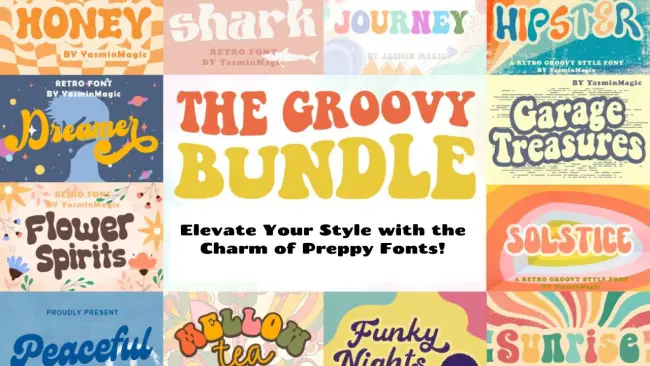
프레피 폰트의 매력으로 스타일을 업그레이드해보세요!
모든 픽셀과 곡선이 중추적인 역할을 하는 역동적인 디자인 영역에서 글꼴의 중요성은 아무리 강조해도 지나치지 않습니다. 글꼴은 단어에 생명을 불어넣어 브랜드와 개인 모두의 시각적 내러티브를 형성하는 숨은 영웅입니다.
타이포그래피의 우아함을 탐구하면서 우리는 세련됨과 유쾌함을 자연스럽게 결합한 독특한 장르인 "Preppy Fonts" 의 매혹적인 세계를 탐구합니다. 화면이나 페이지의 단순한 글자를 넘어, 프레피 글꼴은 전통적인 경계를 뛰어넘는 디자인 철학을 구현합니다.
의도적인 글꼴 선택은 종종 눈에 띄지 않는 방식으로 스타일과 미적 매력에 영향을 미치는 조용한 오케스트레이터가 될 수 있습니다. "Preppy Fonts" 에 담긴 매력을 풀고 디자인의 시각적 언어에 미치는 심오한 영향을 탐구하면서 글꼴의 정교함이 중심이 되는 여정에 동참하세요.
Preppy 글꼴 공개
디자인 세계에서 조용하지만 강력한 커뮤니케이터인 타이포그래피는 "프레피 폰트"에서 그 매력과 세련미를 구현합니다. 이 섹션에서는 프레피 글꼴을 인기 있는 선택으로 만드는 뚜렷한 특징과 뉘앙스를 설명하고 프레피 글꼴의 정의, 특징, 차별화되는 고유한 특성을 검토합니다.
프레피 폰트의 정의와 특징
프레피 글꼴의 핵심은 시대를 초월한 우아함과 현대적인 즐거움의 융합을 보여줍니다. 깔끔한 선, 날카로운 모서리, 세련된 미학으로 정의된 이 글꼴은 세련된 라이프스타일의 본질을 담고 있습니다.
프레피 글꼴의 특징에는 질서정연함, 형식적인 느낌, 다양한 디자인 상황에 대한 다재다능한 적응성이 포함되는 경우가 많습니다.
클래식하면서도 현대적인 분위기를 전달하는 능력 덕분에 프레피 글꼴은 전통 미학과 현대 미학 사이의 균형을 맞추려는 디자이너에게 역동적인 선택이 됩니다.
인기 있는 Preppy 글꼴의 예
프레피 글꼴의 폭과 다양성을 진정으로 이해하려면 구체적인 예를 살펴보는 것이 중요합니다. 시대를 초월한 세리프체를 지닌 "Garamond" 나 높은 대비와 수직 강세로 유명한 "Bodoni" 와 같은 글꼴은 프레피 글꼴 미학의 예입니다. “Helvetica Neue”는 깔끔하고 현대적인 외관으로 유명한 또 다른 다목적 프레피 글꼴입니다.
이러한 각 예는 프레피 글꼴 카테고리에 독특한 풍미를 더해주며, 이 스타일이 독특한 매력을 유지하면서 다양한 디자인 요구 사항에 어떻게 적응할 수 있는지 보여줍니다.
Preppy 글꼴은 다른 타이포그래피 스타일과 어떻게 다른가요?
프레피 글꼴은 우아함을 추구하는 동시에 미묘하면서도 영향력 있는 방식으로 다른 타이포그래피 스타일과 차별화됩니다. 고정폭 글꼴의 구조화된 균일성과 비교하여 프레피 글꼴은 더욱 역동적이고 표현력이 풍부한 시각적 경험을 제공합니다.
손글씨 스크립트 글꼴의 유려하고 개인화된 특성과 달리 프레피 글꼴은 세련되고 세련된 느낌을 유지합니다. 이 섹션에서는 프레피 글꼴을 돋보이게 만드는 특정 속성을 자세히 살펴보고 다른 타이포그래피 스타일과 비교하여 적응성과 독특한 디자인 기여도를 강조합니다.
프레피 폰트의 매력
타이포그래피 영역에서 “Preppy Fonts”의 매력은 단순한 시각적 요소를 넘어 확장됩니다. 이는 시대를 초월한 매력, 문화적 중요성, 브랜드 아이덴티티에 대한 영향력 있는 역할을 반영하는 독특한 매력을 담고 있습니다.
시대를 초월한 프레피 미학의 매력 탐구
프레피 글꼴의 중심에는 디자인 트렌드를 초월하는 시대를 초월한 매력이 있습니다. 깔끔한 라인, 균형 잡힌 비율, 세심한 디테일은 수십 년 동안 지속되는 미학에 기여합니다.
프레피 글꼴에 내재된 단순함과 우아함은 클래식한 세련미를 자신의 작품에 불어넣고자 하는 디자이너에게 영원한 선택이 됩니다. 끊임없이 진화하는 디자인 환경에서 프레피 글꼴은 지속적인 스타일의 확고한 상징으로 자리잡고 있습니다.
문화 협회와 프레피 스타일의 역사
프레피 글꼴의 매력을 진정으로 이해하려면 프레피 스타일의 문화적 연관성과 풍부한 역사를 탐구해야 합니다.
20세기 초 엘리트 아이비리그 대학에서 시작된 프레피 스타일은 세련미, 교육, 절제된 럭셔리함의 대명사가 되었습니다.
이러한 문화적 배경은 프레피 글꼴에 명성과 전통을 불어넣어 미학을 전달할 뿐만 아니라 현대와 시대를 초월한 것을 연결하는 역사적인 이야기를 전달하는 선택이 됩니다.
Preppy 글꼴이 브랜드 아이덴티티와 커뮤니케이션을 강화하는 방법
브랜딩 비즈니스에서는 모든 세부 사항이 중요하며 글꼴 선택은 브랜드 아이덴티티와 커뮤니케이션을 형성하는 데 중추적인 역할을 합니다. 세련되고 세련된 분위기를 지닌 프레피 글꼴은 세련미와 신뢰성을 전달하려는 기업에 다양한 도구를 제공합니다.
마케팅 자료, 로고, 디지털 콘텐츠 등 무엇에서든 프레피 글꼴을 사용하면 전문성과 세부 사항에 대한 관심을 전달하는 시각적 언어를 구축할 수 있습니다. 고정폭 글꼴의 뚜렷한 균일성이나 손글씨 스크립트 글꼴의 개인화된 터치와는 대조적으로, 프레피 글꼴은 독특한 브랜드 특성을 유지하면서 광범위한 청중의 관심을 끌 수 있는 균형을 유지합니다.
디자인에 Preppy 글꼴 통합하기
“Preppy Fonts”를 디자인에 통합하려면 글꼴의 특성뿐만 아니라 다양한 디자인 요소와의 원활한 정렬을 고려하는 미묘한 접근 방식이 필요합니다.
이 섹션에서는 프레피 글꼴을 디자인 프로젝트에 통합할 때 효과적인 전략, 성공적인 예, 필수 해야 할 일과 하지 말아야 할 일을 살펴봅니다.
Preppy 글꼴을 다양한 디자인 요소와 결합하는 팁
프레피 글꼴을 다른 디자인 요소와 결합하려면 균형과 조화에 대한 예리한 안목이 필요합니다. 대담한 프레피 글꼴과 세련되고 미니멀한 레이아웃을 대조하여 눈에 띄는 시각적 효과를 만들어보세요.
또는 세리프 프레피 글꼴과 우아한 일러스트레이션을 결합하면 고전적인 세련미를 불러일으킬 수 있습니다. 가독성과 전반적인 시각적 매력을 향상시키는 보완적인 대비를 위해 노력하십시오.
고정 폭 글꼴의 엄격한 균일성이나 손글씨 스크립트 글꼴의 흐르는 듯한 특성과 달리 프레피 글꼴은 페어링에 유연성을 제공하므로 광범위한 디자인 응용 프로그램에 적합합니다.
Preppy 글꼴을 사용한 성공적인 디자인 프로젝트의 예
프레피 글꼴이 다양한 디자인 상황에서 어떻게 빛날 수 있는지 이해하려면 실제 사례를 검토하는 것이 중요합니다. J.Crew 및 Ralph Lauren과 같은 브랜드는 프레피 글꼴을 활용하여 시대를 초월한 우아함을 전달하고 로고, 포장 및 마케팅 자료에 원활하게 통합합니다.
웹 디자인에서 Pinterest와 같은 플랫폼은 프레피 글꼴을 사용하여 깨끗하고 세련된 미학을 유지하여 향상된 사용자 경험에 기여합니다. 이러한 예는 다양한 업계에 걸쳐 프레피 글꼴의 다양성을 보여주고 브랜드 아이덴티티를 전달하는 데 있어 그 효과를 보여줍니다.
Preppy 글꼴을 사용할 때 해야 할 일과 하지 말아야 할 일
프레피 글꼴을 성공적으로 통합하려면 해야 할 일과 하지 말아야 할 일을 따르는 것이 중요합니다.
- 명확한 글자체와 적절한 간격을 갖춘 프레피 글꼴을 선택하여 가독성을 우선시하세요.
- 브랜드의 개성에 맞는 조합을 찾으려면 글꼴 조합을 실험해 보세요.
- 장식 요소를 과도하게 사용하지 마십시오. 고유한 우아함을 지닌 프레피 글꼴은 그 자체로 돋보일 때 빛을 발하는 경우가 많습니다.
- 계층 구조와 일관성의 중요성을 무시하지 마십시오. 다양한 디자인 요소에 걸쳐 응집력 있는 모양을 유지하여 전반적인 효과를 향상시킵니다.
디자이너는 이러한 해야 할 일과 하지 말아야 할 일을 준수함으로써 프레피 글꼴의 잠재력을 최대한 활용하여 시각적으로 매력적이고 효과적인 디자인 프로젝트를 만들 수 있습니다.
디지털 시대의 프레피 글꼴
컴퓨터화된 장면을 탐색하면서 "Preppy Text 스타일" 작업이 현대 계획의 요구 사항을 충족하도록 개발되었습니다.
이 세그먼트에서는 웹 및 고급 계획에서 프레피 텍스트 스타일의 중요성을 조사하고, 이러한 텍스트 스타일을 찾고 사용하기 위한 장치 및 자산에 대한 약간의 지식을 제공하며, 프레피 텍스트 스타일이 가상 엔터테인먼트 및 사이트의 느낌을 어떻게 향상시킬 수 있는지 자세히 알아봅니다.
온라인 및 디지털 디자인에서 Preppy 글꼴의 관련성
화면이 지배하는 시대에 프레피 글꼴은 고전적인 미학과 현대적인 매력을 완벽하게 결합하여 관련성을 유지합니다. 프레피 글꼴 고유의 깔끔한 라인과 시대를 초월한 우아함은 온라인 및 디지털 플랫폼으로 원활하게 변환되어 세련되고 정교한 사용자 경험에 기여합니다.
프레피 글꼴의 적응성은 웹사이트 제목부터 소셜 미디어 그래픽에 이르기까지 다양한 디지털 애플리케이션에서의 효율성을 보장합니다. 고정 폭 글꼴의 실용적인 성격이나 손글씨 스크립트 글꼴의 비공식적인 매력과 달리 프레피 글꼴은 디지털 영역에서 잘 어울리는 전문성을 제공합니다.
Preppy 글꼴을 찾고 사용하기 위한 도구 및 리소스
디지털 프로젝트에 적합한 프레피 글꼴을 찾으려면 다양한 서체에 액세스해야 합니다. 다행히도 수많은 도구와 리소스가 프로세스를 단순화합니다. Google Fonts 및 Adobe Fonts와 같은 플랫폼은 디지털 디자인에 쉽게 통합할 수 있는 광범위한 프레피 글꼴을 제공합니다.
디자이너는 글꼴 라이브러리를 탐색하여 디지털 인터페이스 및 반응형 디자인과의 호환성을 보장할 수 있습니다. 프레피 글꼴의 다양성은 실험과 사용자 정의를 가능하게 하여 디자이너가 디지털 창작물에 완벽하게 어울리는 글꼴을 찾을 수 있도록 해줍니다.
Preppy 글꼴이 소셜 미디어와 웹사이트 미학을 향상시키는 방법
소셜 미디어와 웹사이트 디자인의 역동적인 세계에서 프레피 글꼴은 관심을 끌고 브랜드 미학을 향상시키는 독특한 터치를 제공합니다.
소셜 미디어 그래픽, 배너, 웹 사이트 제목에 프레피 글꼴을 활용하면 전체적인 시각적 매력을 향상시켜 일관되고 기억에 남는 브랜드 아이덴티티를 만들 수 있습니다. 프레피 글꼴의 구조화된 특성은 디지털 화면의 가독성에 기여하여 긍정적인 사용자 경험을 보장합니다.
결론
디자인의 교향곡에서 우리는 "Font Finesse: 프레피 글꼴의 매력으로 스타일 향상"의 뉘앙스를 살펴보았습니다. 프레피 글꼴의 정의와 특징을 밝히는 것부터 디지털 시대에서의 관련성을 탐구하는 것까지, 우리는 고정 폭 글꼴이나 손글씨 스크립트 글꼴과 차별화되는 세련미와 현대적인 매력의 독특한 조화를 목격했습니다.
이 탐구를 마무리하면서 디자이너와 창작자 여러분을 프로젝트에 프레피 글꼴의 매력을 활용해 보시기 바랍니다. 깔끔한 라인과 시대를 초월한 우아함을 실험하고 디지털 활동에서 브랜드의 목소리가 되거나 시각적 멜로디가 되도록 하세요.